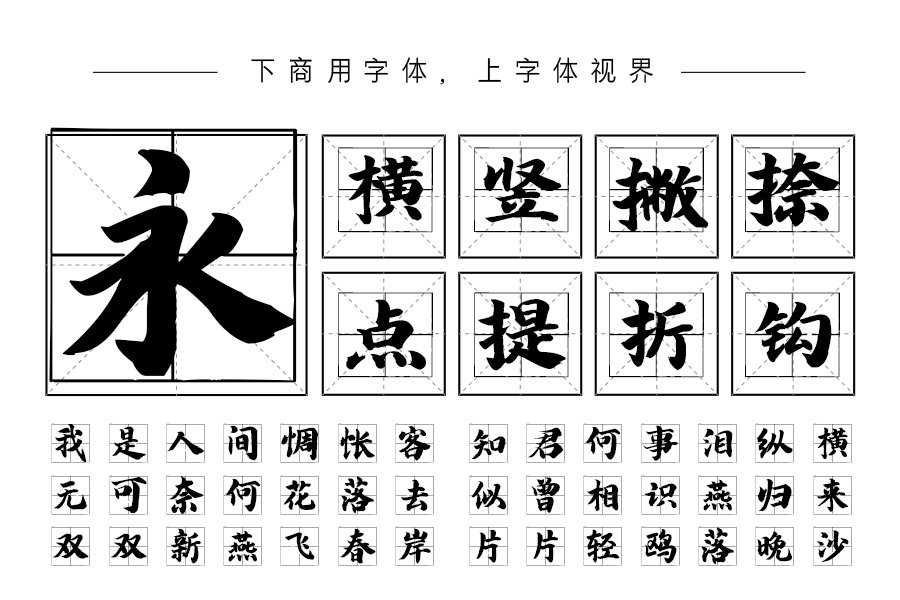
汉呈王天喜古风体是由汉呈字库全新推出的手写书法字体,该字体已经在字体视界上线,并且取得「汉呈王天喜古风体」字体的官方代理授权,有权为您提供字体授权服务。
该字体的起笔和收笔处的修饰部分,更加圆融,不仅适合了小屏幕手机显示的特性,而且注入了现代质感因素,横笔画与竖笔画比例更加和谐美观。其字体看上去非常的端正秀美,充满了古典气息,并看上去非常的端正秀美,充满了古典气息。可以很好的应用于信息展示、网页设计、平面宣传设计。